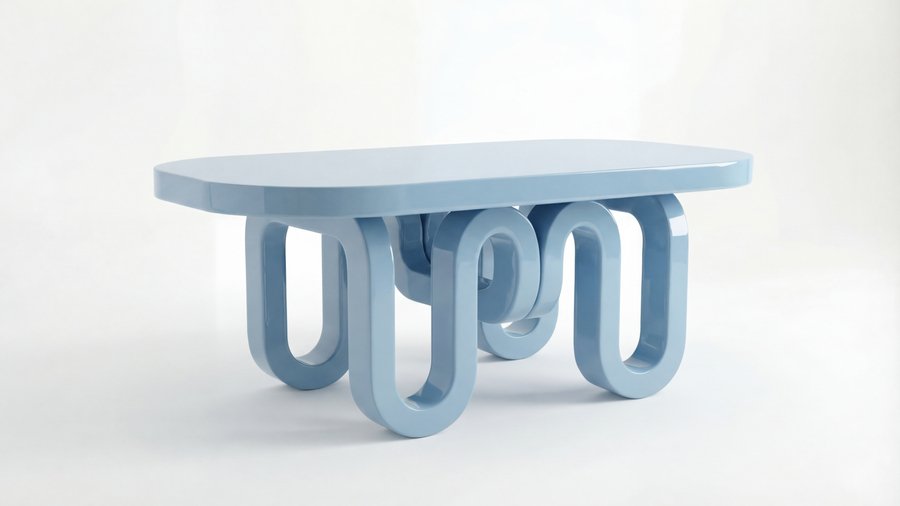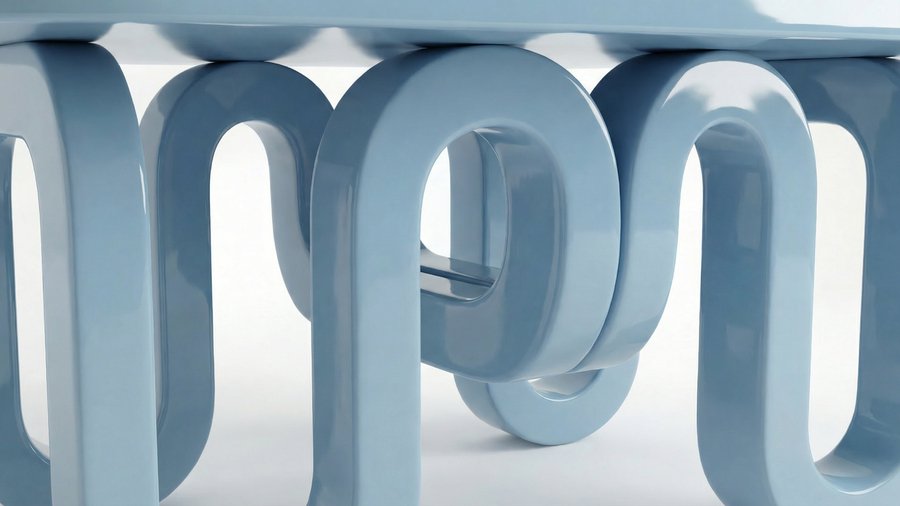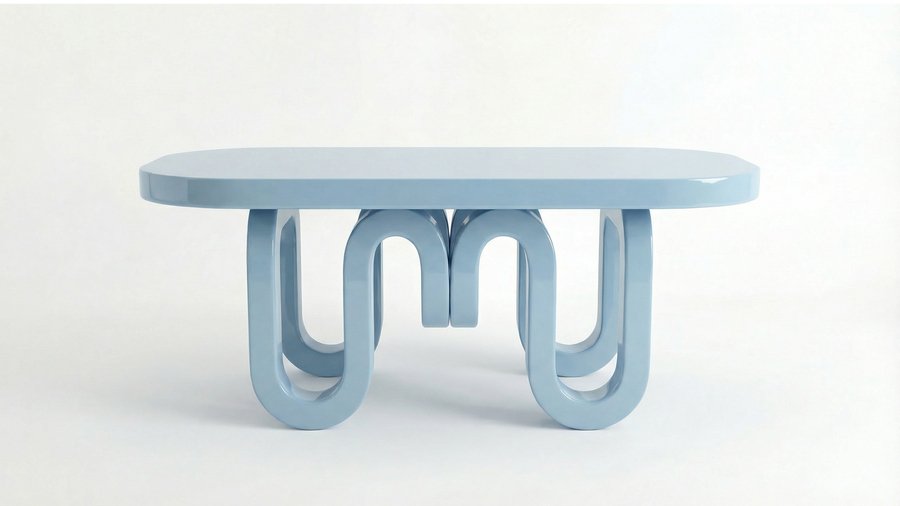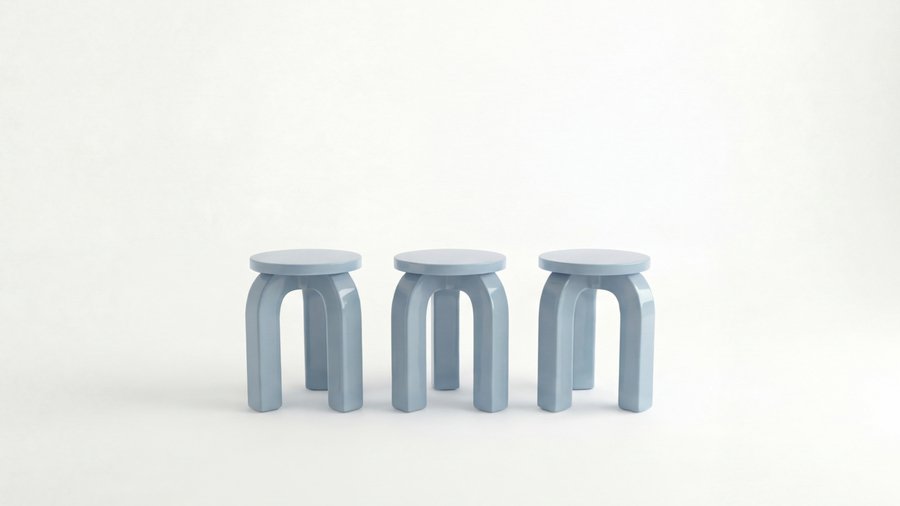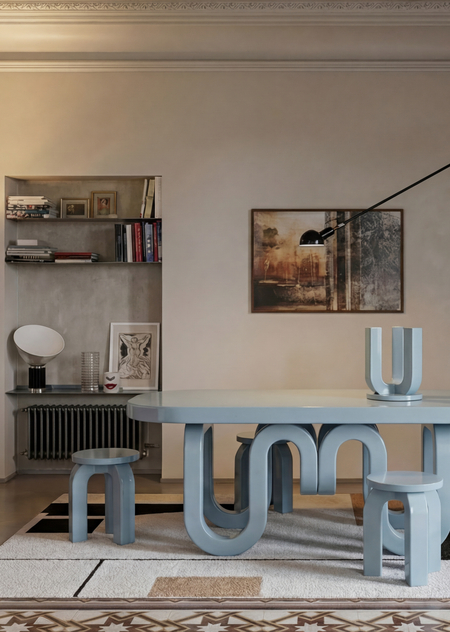
В состав коллекции входят: обеденный стол и табуретка; проект объединяет графические формы авторского акцидентного шрифта «ini font» и функциональные объекты, превращая абстрактные формы в практичные элементы интерьера